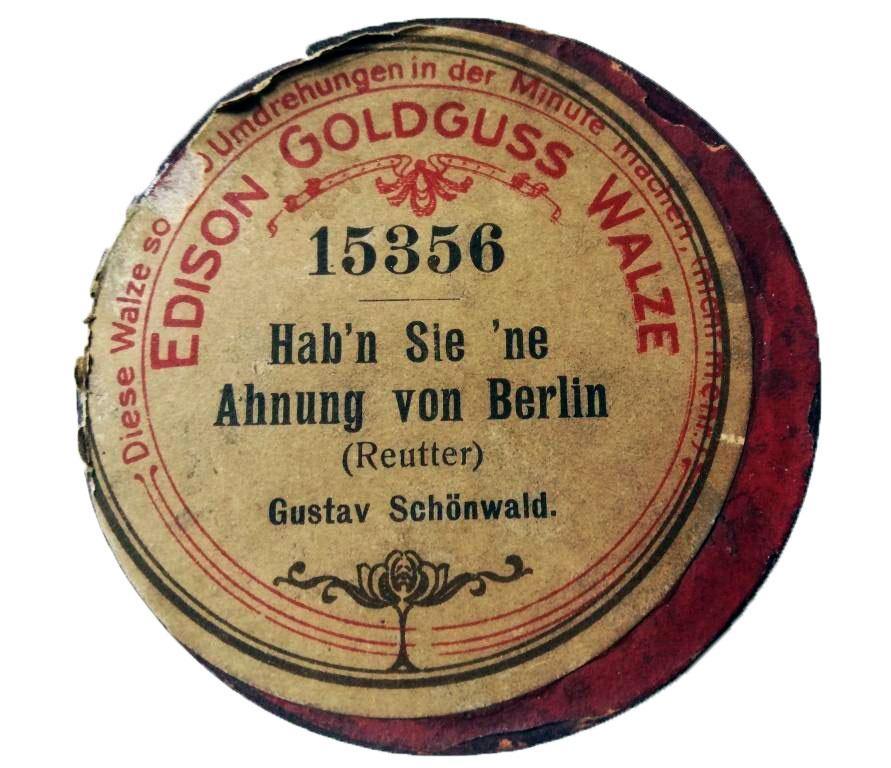
Schriften auf Edison Walzen Verpackung
Welche Schriften könnten denen der Edison Goldguss Walzen Verpackung entsprechen. Zeit etwa 1905.
Damals:
Made at Wagner & Schmidt in 1880 and cast as Schmale Etienne by Bauer and J. John. Also sold as Schmale fette Etienne by Berthold, Haas, and Stempel; as Halbfette Etienne by Schriftguss AG; as Fette Etienne by Gebr. Arndt [Wetzig 1926–40] and as Vette verlengde Etienne by Amsterdam. Shown in a specimen by FTF from 1920 as Estienne (used for the sample). It is not clear which foundry issued the original version.
Estienne (Solotype) is a digital version that goes back to “just before 1900 in France”.
(Reuter) könnte die Elzevir sein, von Gursch oder Berthold. Diese ist meines Wissens nicht direkt digitalisiert worden, aber ähnlich ist die US-amerikanische DeVinne, auf der die Roslindale (ab 2017) von David Jonathan Ross basiert.